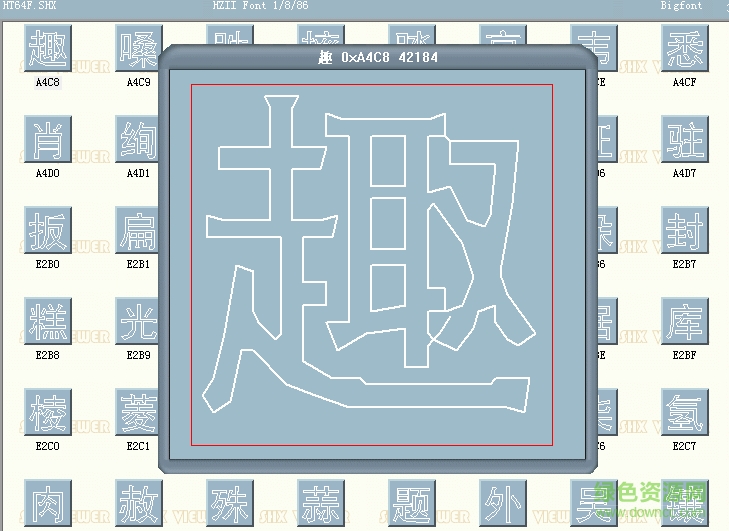
ht64f.shx
ht64f.shx是一款非常好用的cad字體,字體呈雙層夾心狀態(tài),非常的工整美觀,常常會(huì)在cad的設(shè)計(jì)圖紙中出現(xiàn)該字體,用戶下載后就可以在cad繪圖中使用該字體了,也可以順利的查看使用過該字體的圖紙了,歡迎有需要的朋友到綠色資源網(wǎng)下載使用!